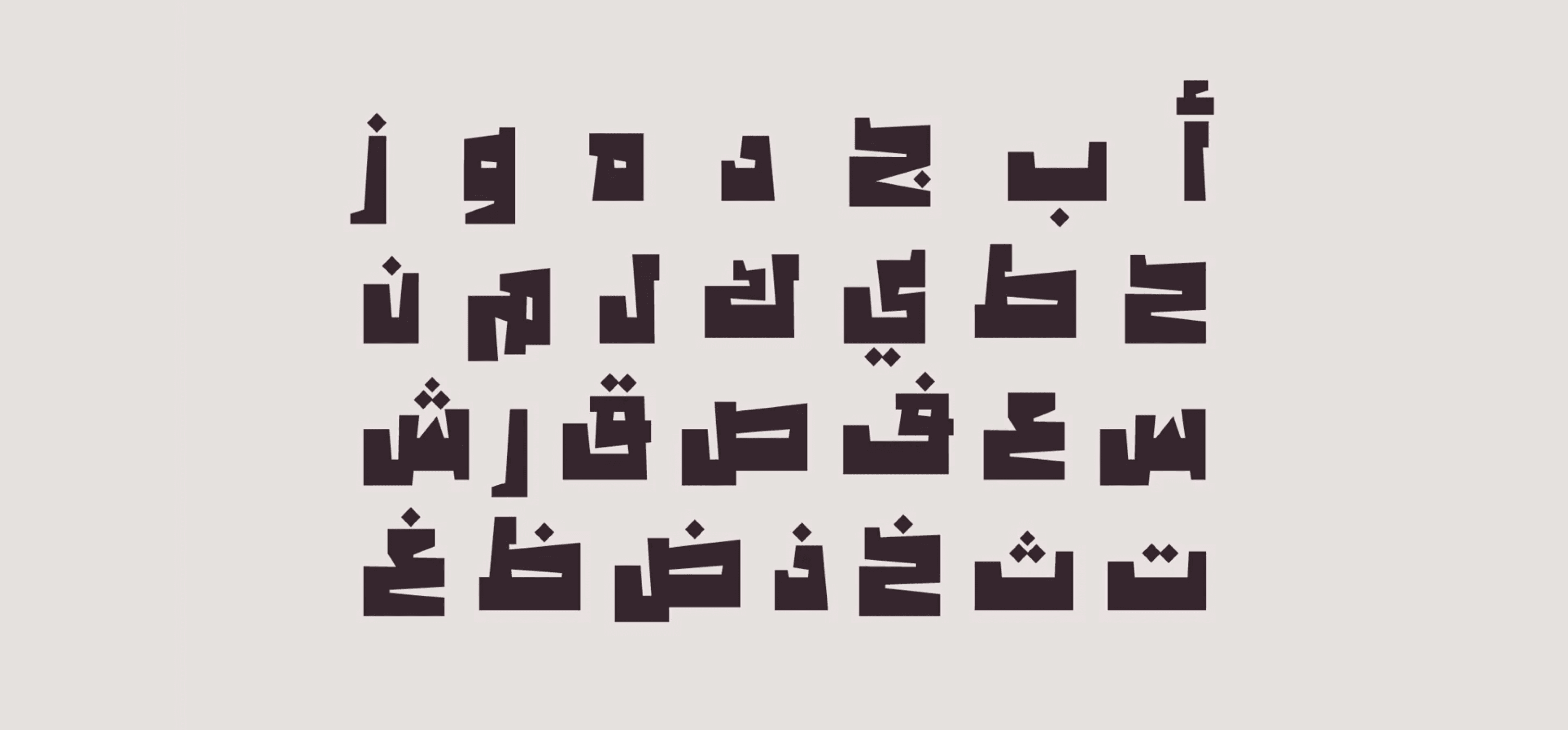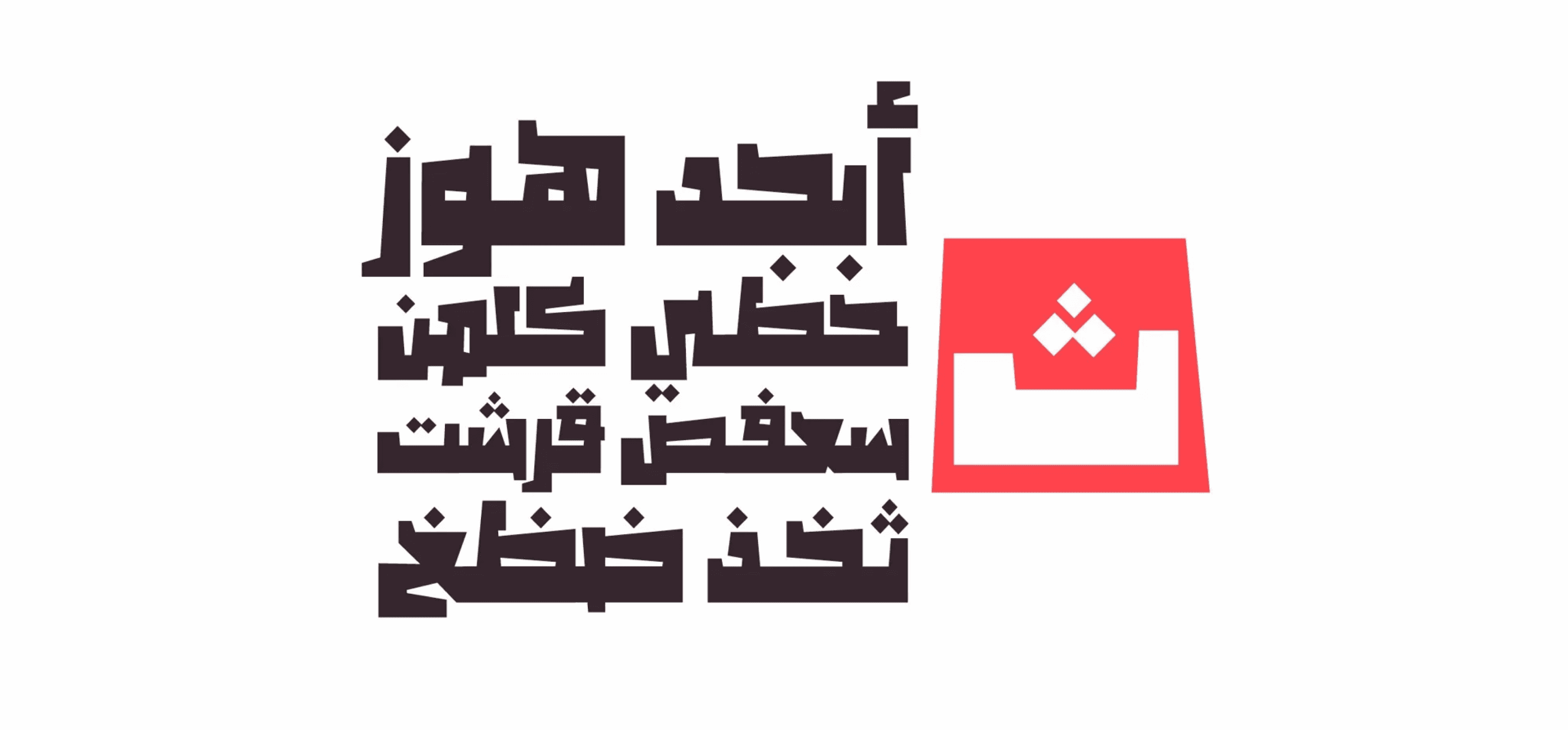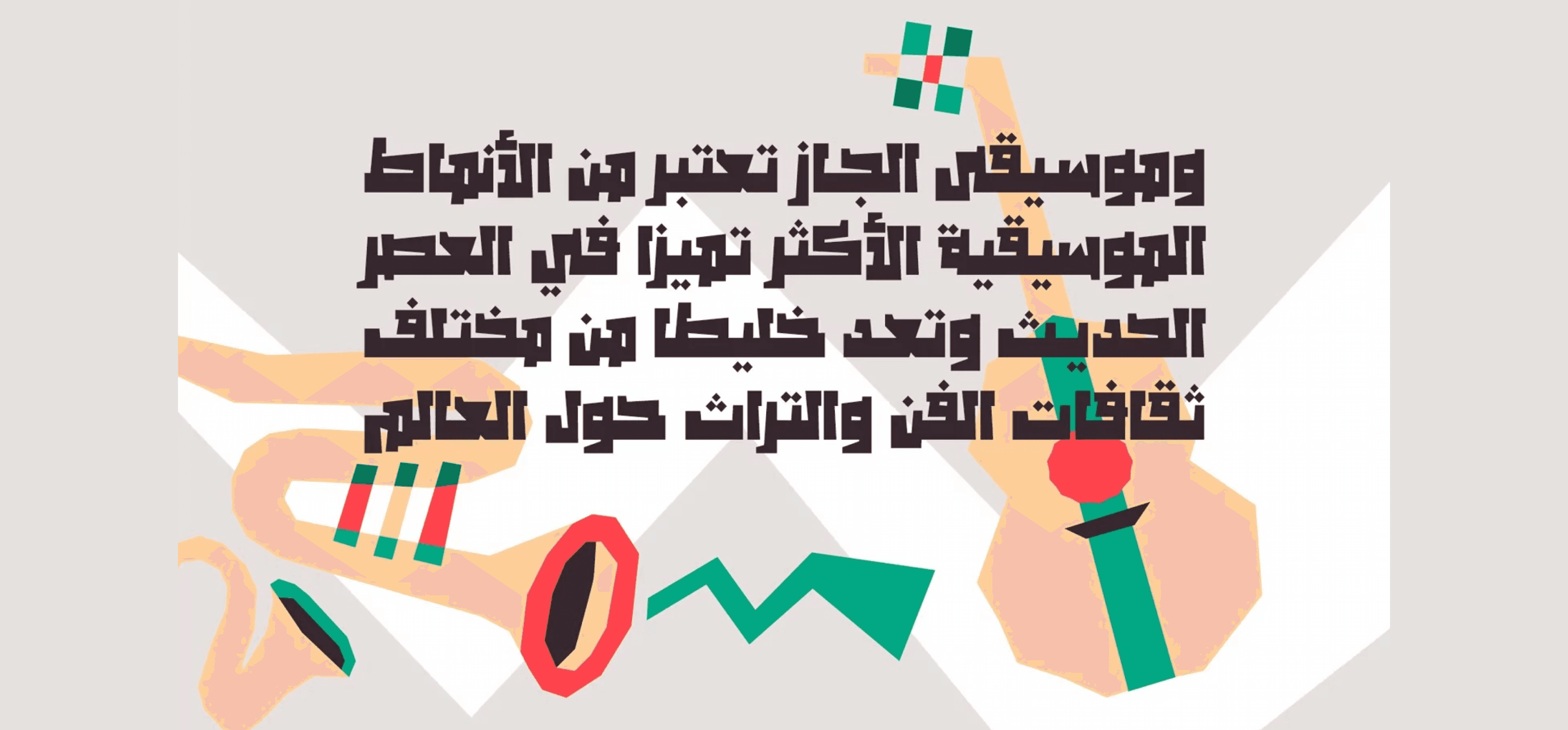
خط Maksoos (وهي كلمة عربية تعني "مقصوص") هو خط عرض عربي يتميز ببنية حروف سميكة ولافتة، ويتوفر بنمطين: Display وOpaque. يناسب الخط المشاريع التصميمية الجريئة مثل المواقع الإلكترونية، المطبوعات، الإعلانات، والعلامات التجارية. كما أنه متوافق مع أنظمة التشغيل ويندوز، ماك، وتطبيقات الهواتف المحمولة.